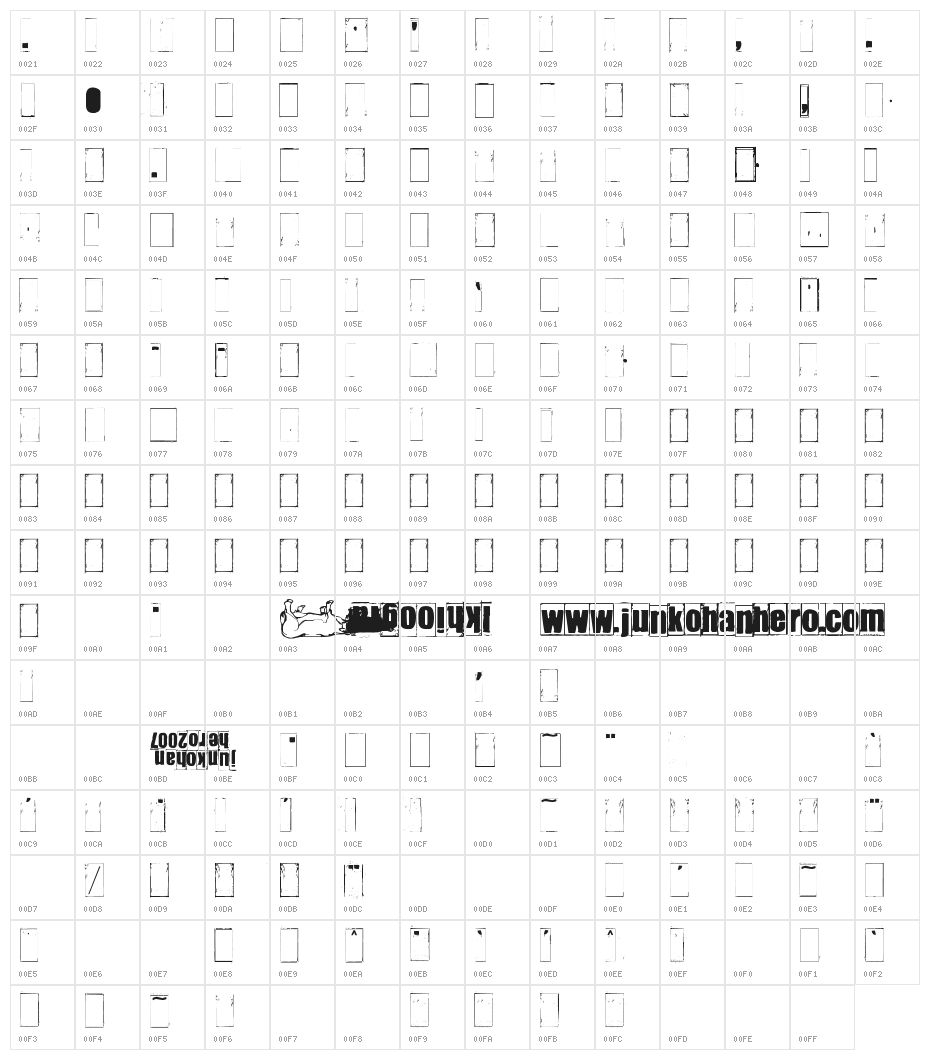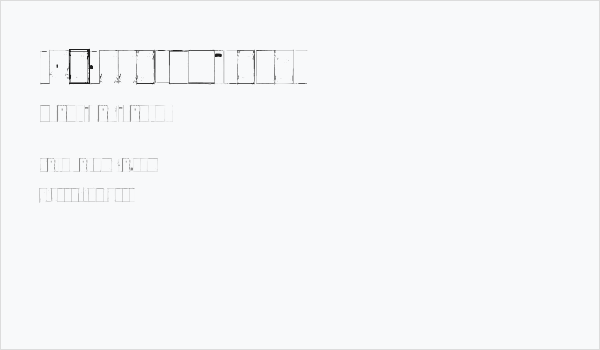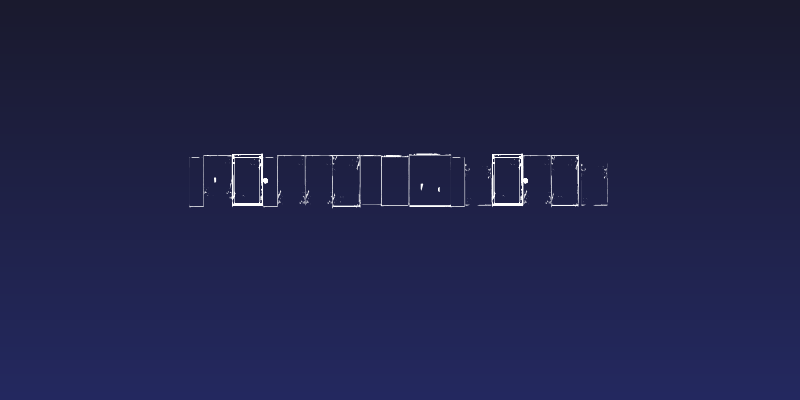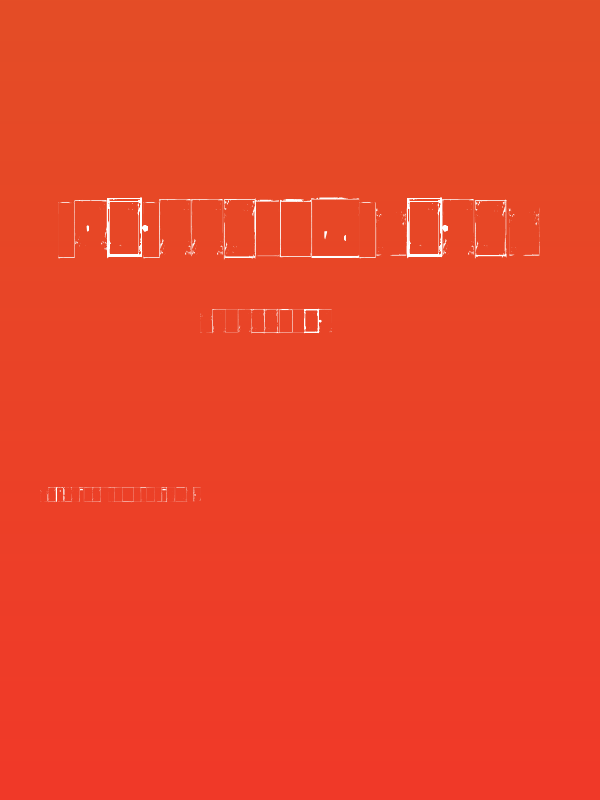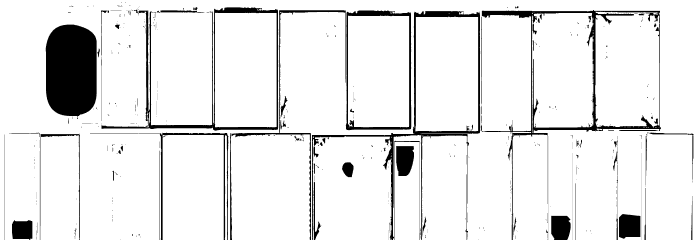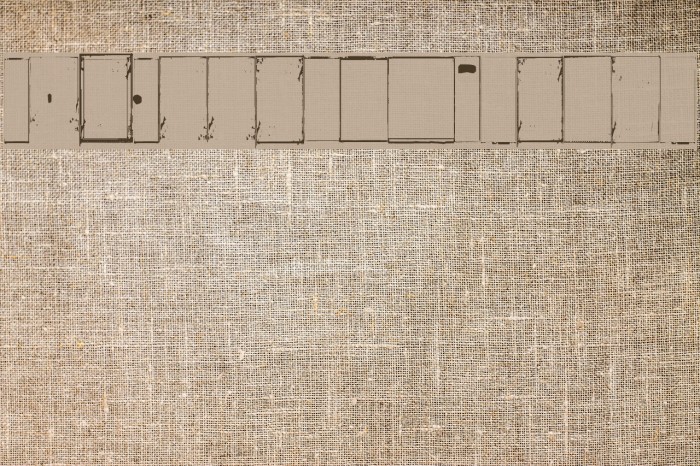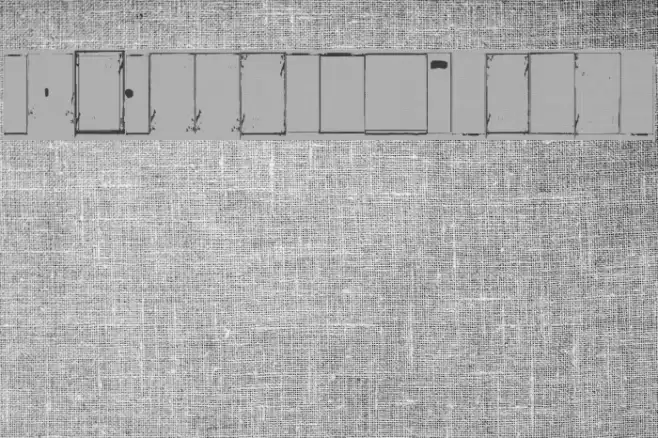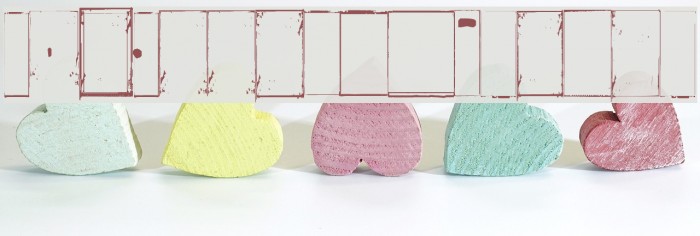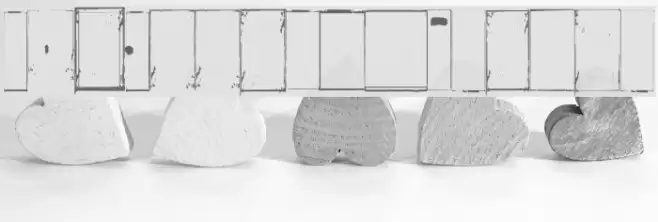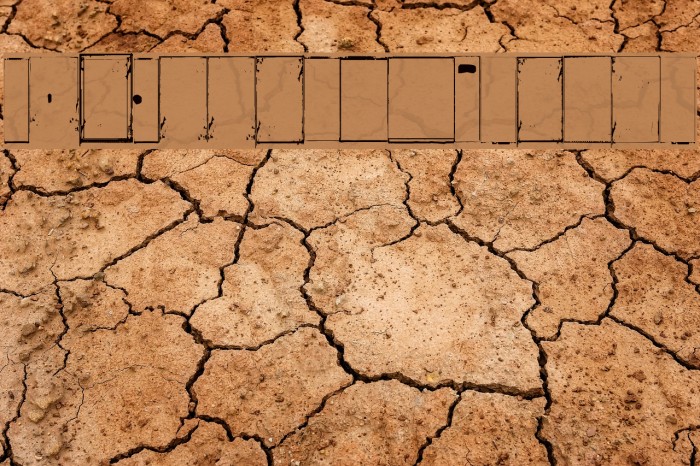
IKHIOOGLAwithout Font
✎ Distorted Eroded
| الفئات | Distorted Eroded |
| النمط العام | Modern, Abstract, Experimental |
| حالة الاستخدام | Logos, Display text, Artistic projects |
| مشاريع مقترحة | Experimental posters, avant-garde branding, album covers, digital art, conceptual design projects. |